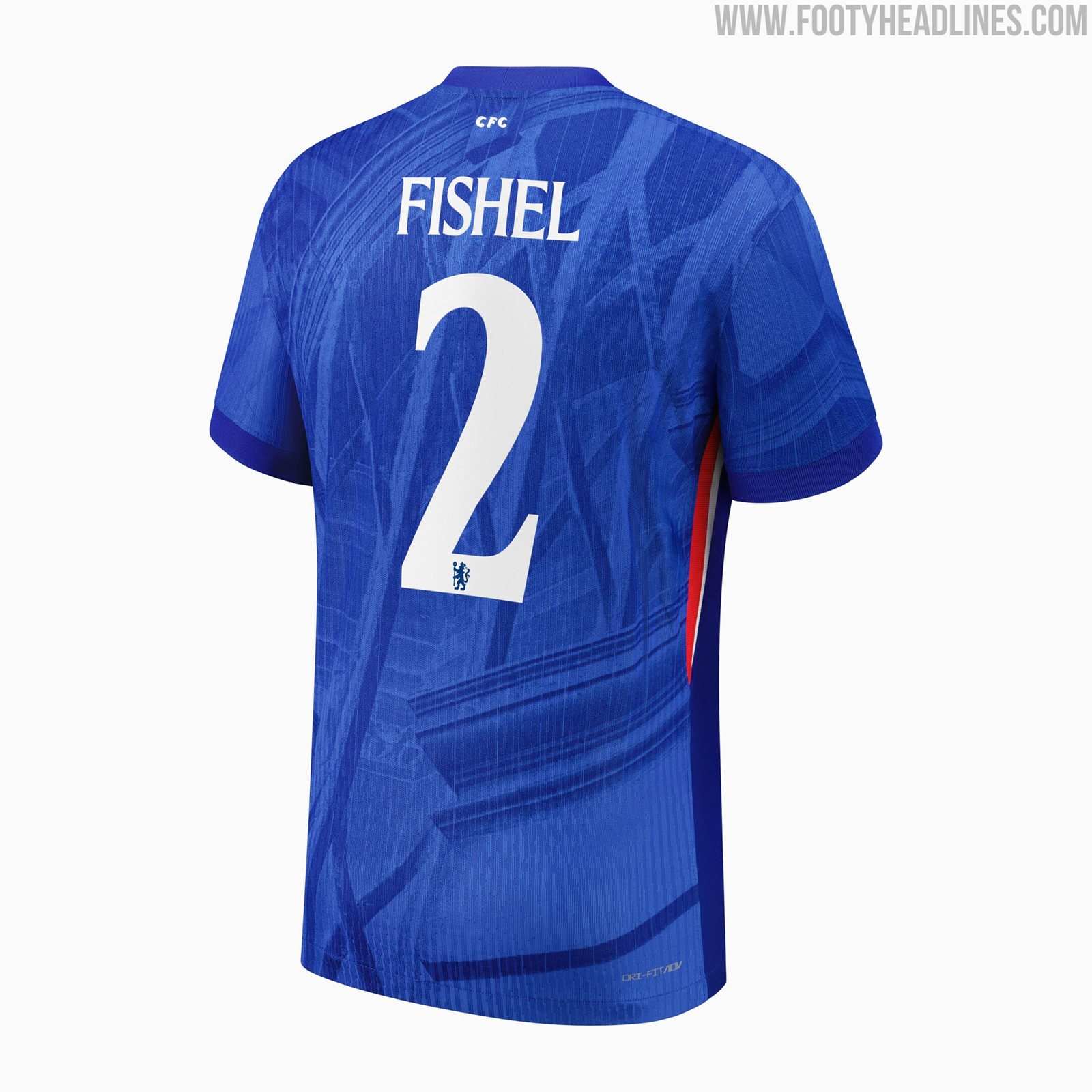
Neue Schriftart für das Chelsea 25-26 Trikot veröffentlicht
• Neue Trikot-Schriftart: Der FC Chelsea wird ab der Saison 2025-26 eine völlig neue Trikot-Schriftart verwenden, die das Design von 2019 ersetzt.
• Modernisiertes Design: Die neue Schriftart zeichnet sich durch eine modernere und mutigere Ästhetik mit eleganteren Kurven und raffinierten Serifen aus.
Der FC Chelsea hat eine völlig neue Trikot-Schriftart vorgestellt, die ab der Saison 2025-26 verwendet wird. Dies ist die erste Aktualisierung der Vereinsschrift seit sechs Jahren. Sie ersetzt das Design, das 2019 vorgestellt wurde und bis zur Saison 2024-25 verwendet wurde.
Völlig neue Chelsea 25-26 Trikot-Schriftart
Das neue Chelsea 25-26 Trikot hat eine modernisierte, mutigere Ästhetik, ohne dabei die traditionelle Identität des Vereins zu vernachlässigen.
Die Ziffern und der Schriftzug sind etwas komprimierter als der vorherige Stil, mit eleganten Kurven und raffinierten Serifen, die der Schrift einen moderneren und dennoch unverwechselbaren Look verleihen.